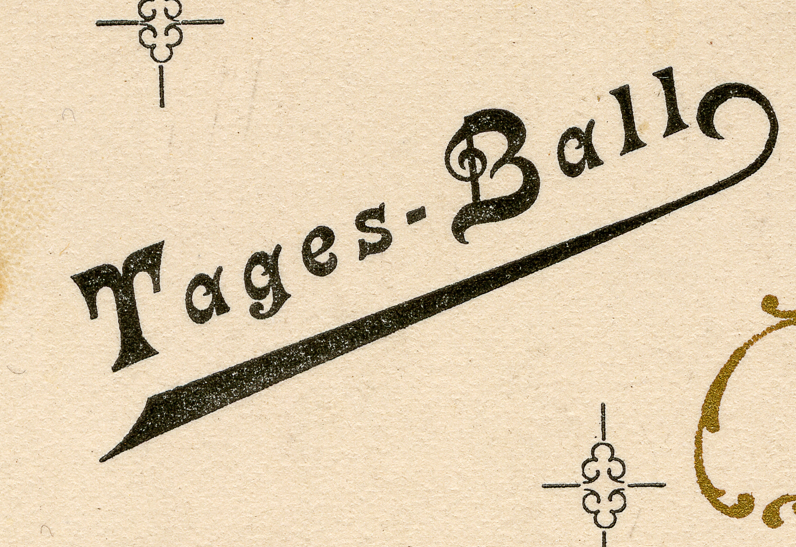
Schriftart von Tischkarte Historismus/Jugendstil 1897
ich bin auf der Suche nach einer Font, die dieser Schriftart entspricht oder zumindest sehr sehr nahe kommt.
Die Schriftprobe stammt von einer Tischkarte für einen Vereinsball vom 14.02.1897. Ich habe diese Schriftart aber auch schon an anderer Stelle gesehen, sie muss also relativ gängig gewesen sein.
Da die gleichen Buchstaben nicht identisch sind, gehe ich von einer Handarbeit und keiner Satzschrift aus.
Ähnliche kenne ich leider keine – schade, ist eine schöne Schrift.
ich würde die unterschiede der gleichen lettern eher auf abnützung zurückführen (oder hab ich was wesentliches übersehen?) und imho sehr wohl auf eine satzschrift tippen.
Ich stimme mich mit Carlito Palm überein. Ich habe die Vergrößerung des Bildes angeschaut und ich gehe davon aus, es handelt sich hier eindeutig auf einer Satzschrift!
Die Crayonette war von mindestens zwei deutschen Schriftgießereien erhältlich (Gronau und Theinhardt, beide in Berlin bzw. Schöneberg). Bei Gronau war die Schrift als Zierschrift Columbia vermarktet, bei Theinhardt Italienne Cursiv.
Gronau tauschte Matrizen mit US-amerikanischen Firmen seit mindesten 1852 aus, vermutlich auch früher. Generell waren die Schriftgießereibesitzer auf beiden Seiten des Atlantiks zumindest ab und zu mit einander brieflich in Kontakt. Es gibt vereinzelten erhaltenen Briefe im Nachlass der Bruce Type Foundry an der Columbia University in New York.